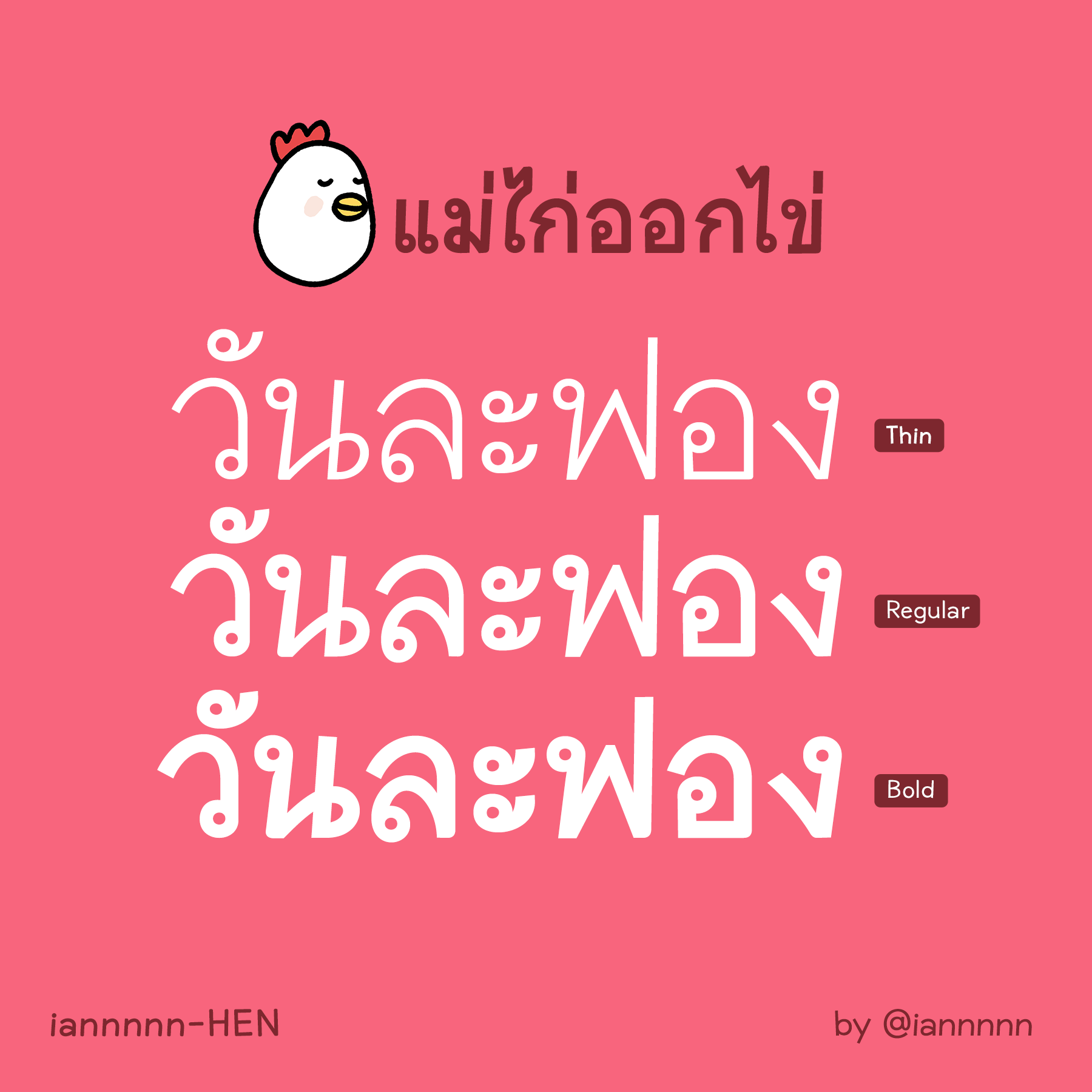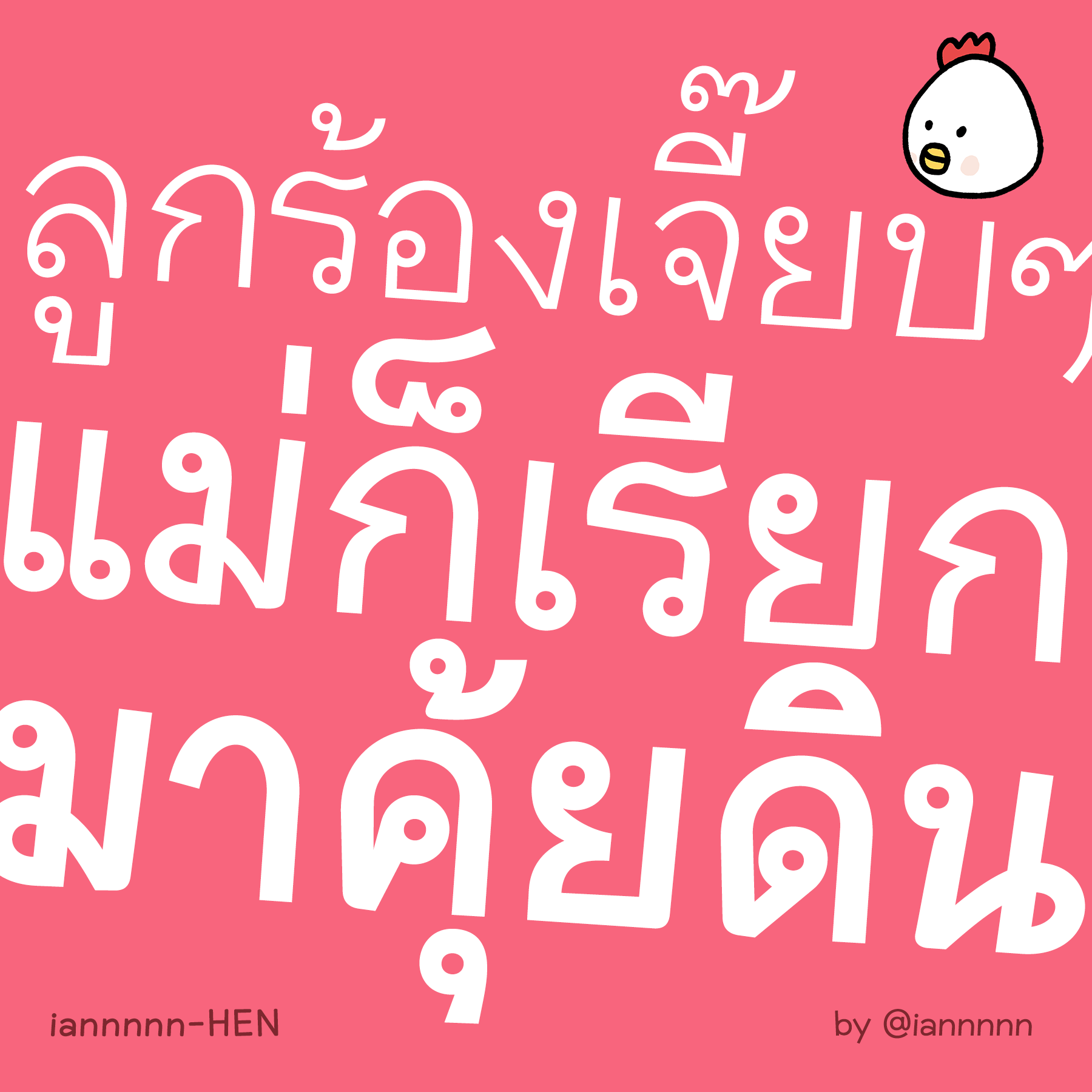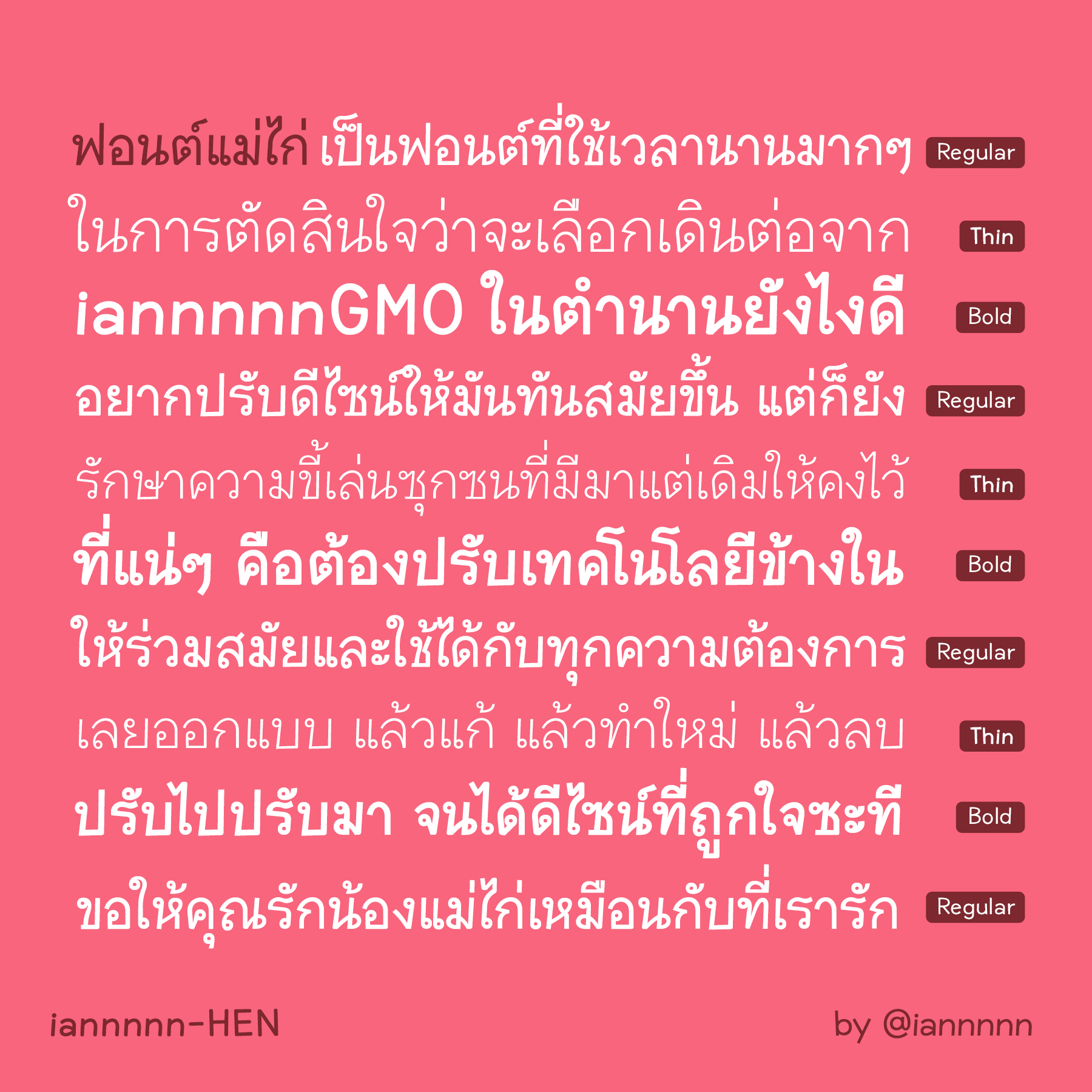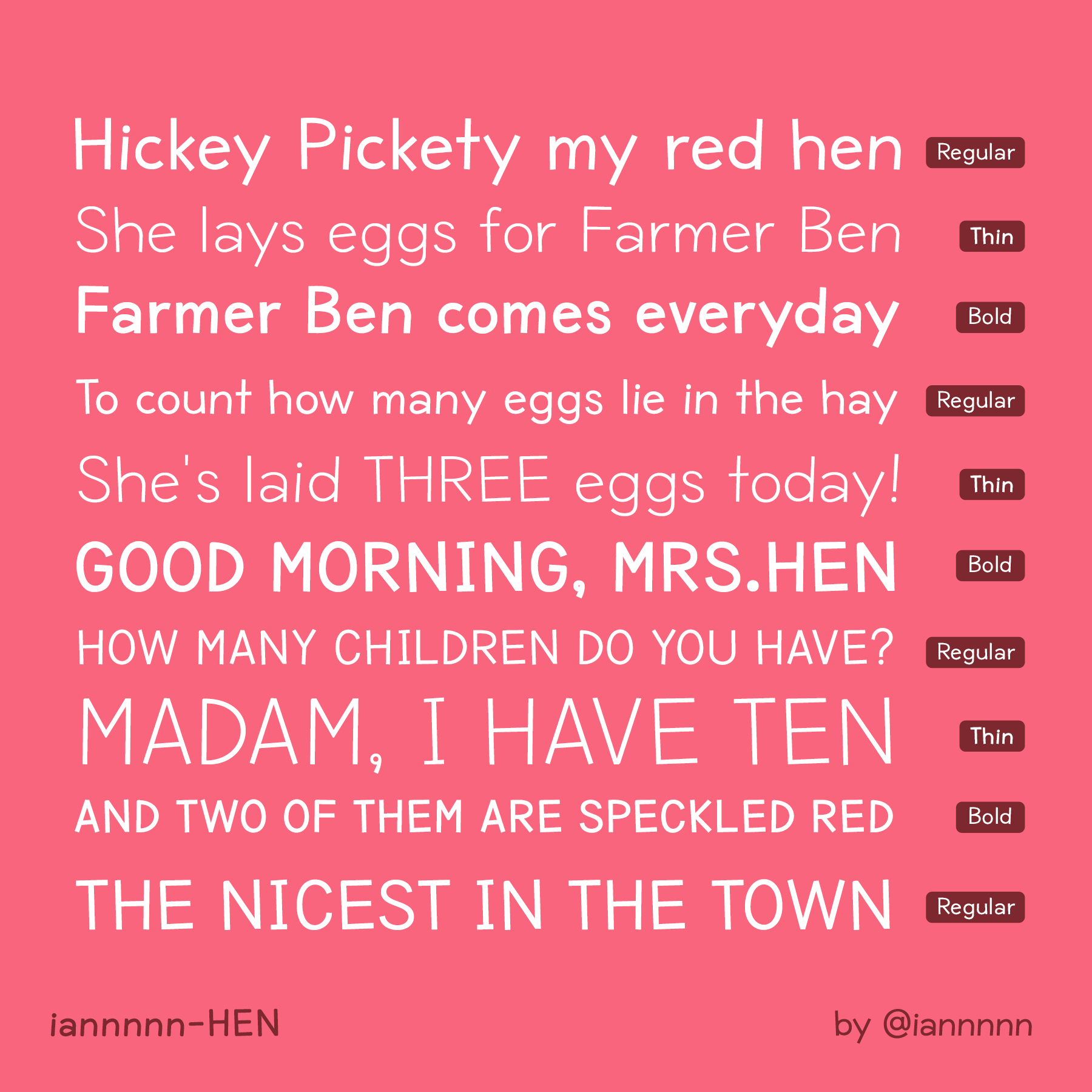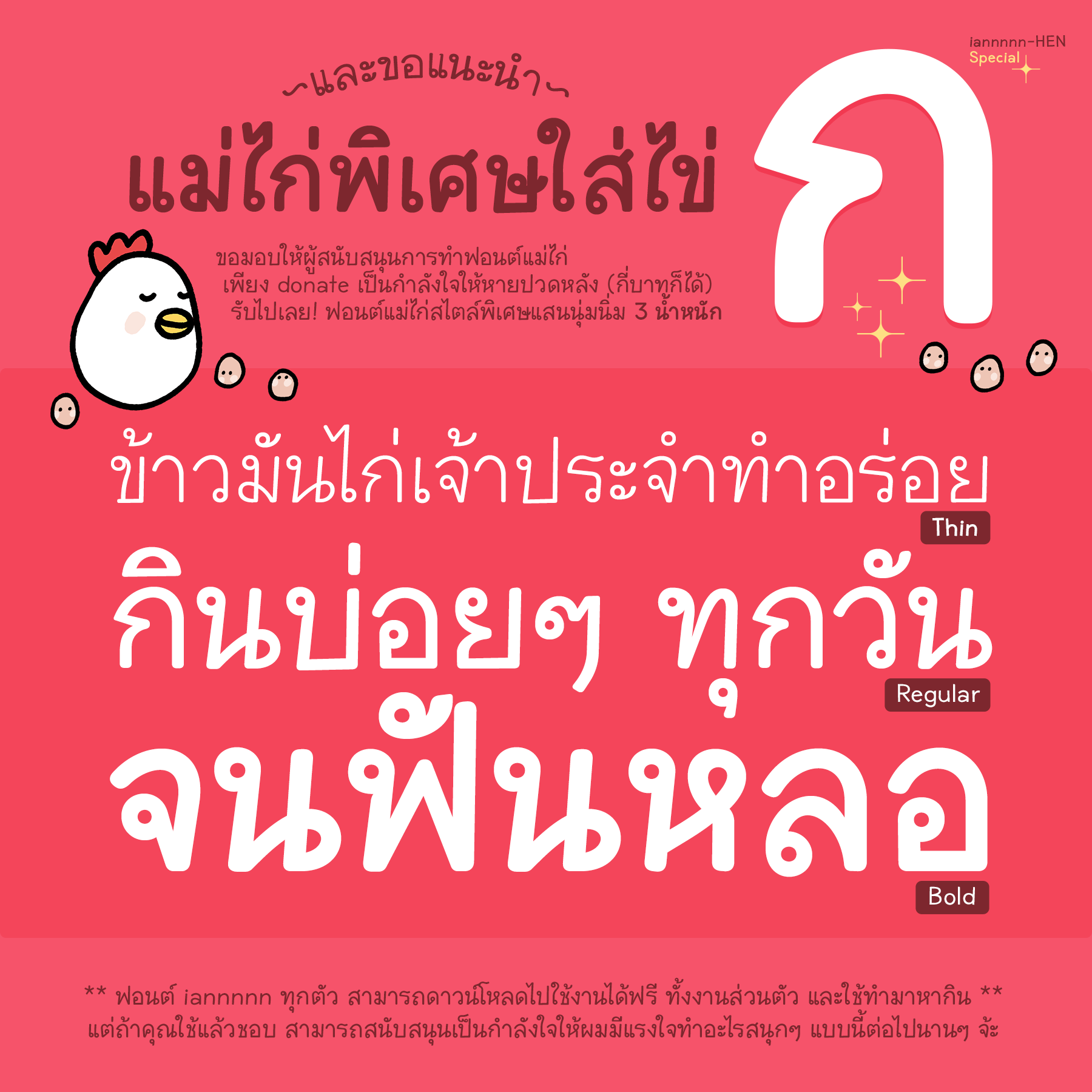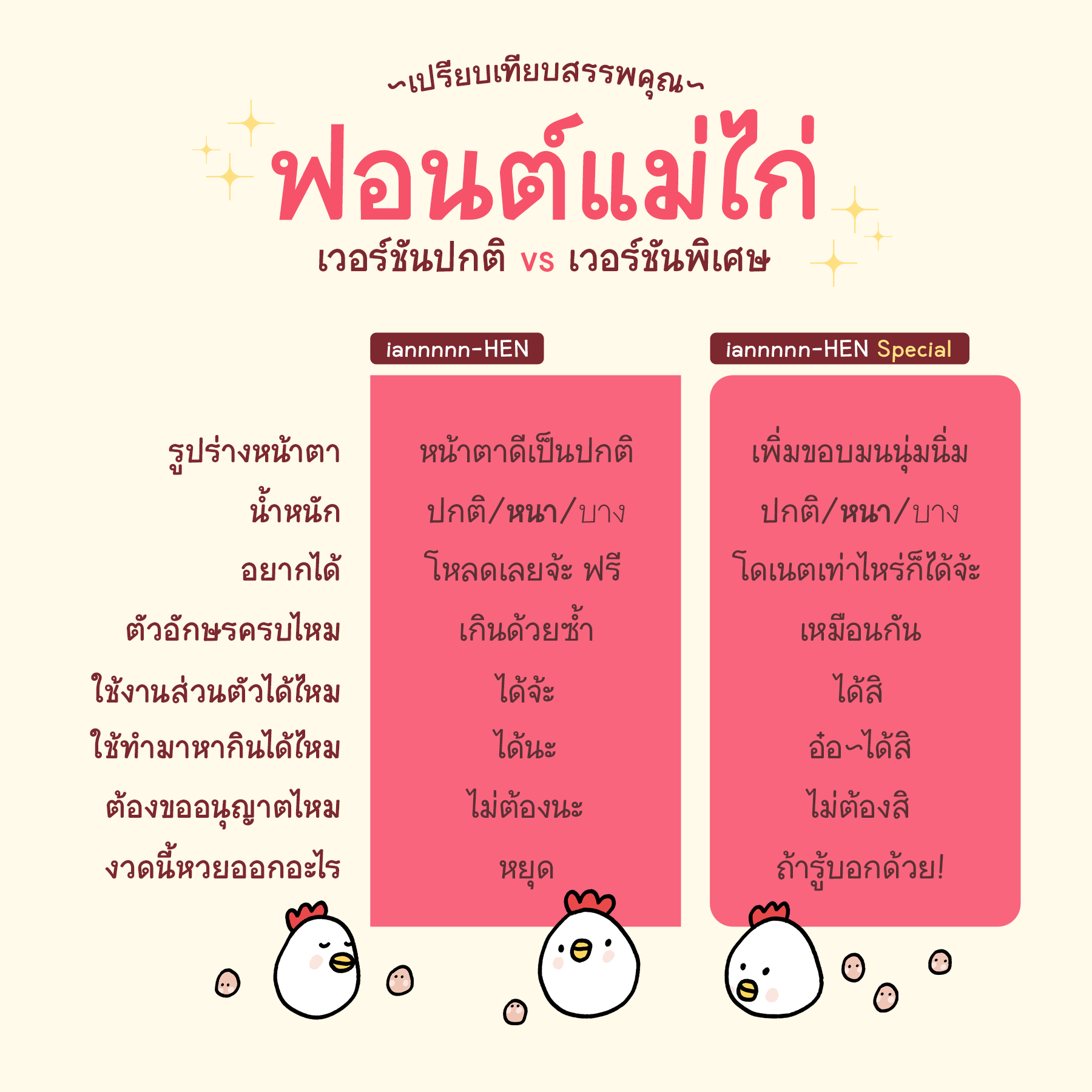
แม่ไก่ (iannnnn-HEN)
ฟอนต์หน้าตาเหมือนจะจริงจัง แต่ก็ยังโย้ไปเย้มา ให้อารมณ์สนุกสนาน เป็นมิตร จั๊กจี้ขี้เล่น ใช้งานได้หลากหลาย ทั้งพาดหัว และตัวเนื้อความ มี 3 น้ำหนัก ทั้งบาง กลาง หนา (และ 3 สไตล์นุ่มพิเศษสำหรับผู้ donate เท่าไหร่ก็ได้)
อยากทำฟอนต์ที่ให้บรรยากาศแบบ iannnnnGMO ที่เคยทำไว้ราวๆ 20 ปีก่อน ถึงจะยังเป็นฟอนต์ที่นิยมใช้งานอยู่ในปัจจุบัน แต่เทคโนโลยีในฟอนต์มันตกยุคไปนานมากแล้ว แถมดีไซน์ก็มีตำหนิเยอะ คนทำเห็นแล้วอาย 5555 เลยขอทำตัวใหม่ขึ้นมา เหมือนเป็นการบูรณะฟอนต์แบบเดียวกับฟอนต์เสือ ที่ทำมาทดแทน iannnnnTKO
พอเริ่มโครงการรื้อดีไซน์ แต่อยากให้ได้กลิ่นเดิม มากไปก็ไม่ชอบ น้อยไปก็ไม่ดี เลยกลายเป็นว่าฟอนต์นี้นั่งทำๆ ลบๆ (ดองๆ) มา 5 ปีครับ จนรู้สึกว่าต้องมูฟออนแล้ว! ก่อนคนทำจะแก่ สายตายาวไปกว่านี้ เลยใช้เวลาว่างหลังงานเสร็จก่อนนอน มาลุยทำวันละนิด วันละหน่อย จนในที่สุดก็สำเร็จออกมาเป็นฟอนต์แม่ไก่ ที่ดูเป็นมิตร ขี้เล่น คือพยายามจริงจังแล้วนะ แต่ได้แค่นี้ 5555555
ฟอนต์ iannnnn-HEN (แม่ไก่)